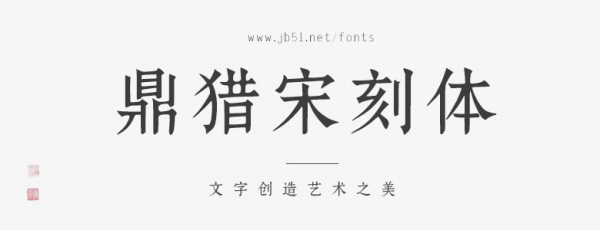
鼎獵宋刻體,源于結體謹嚴,筆畫頓挫感明顯的宋刻本,鼎獵宋刻體排版時文理堅致有韌性,版式疏朗雅潔,適合美食餐飲、文化藝術展覽、企業(yè)文化,以及封面雜志海報、餐飲茶飲、美妝護膚等各個行業(yè)。馬上踏入2025年了,這套字體姍姍來遲,終于到了發(fā)布的時候。
考慮到字體應盡可能滿足各類型應用場景,鼎獵宋刻體以簡體中文漢字編碼國家標準(GB2312編碼)為標準,共計設計了多達7415個字符,其中漢字6769個??梢詽M足絕大部分印刷設計等要求。